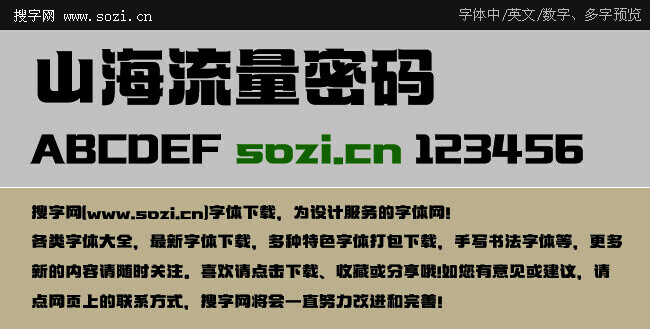
山海流量密碼
搜字網(wǎng)提供一款山海流量密碼中文藝術(shù)字體下載,山海流量密碼是一款醒目的藝術(shù)字體,包含簡體漢字6763個(gè)。該字體線條粗壯醒目,筆畫簡潔自然,字體的視覺效果有力、寬厚、方正,充滿了穩(wěn)重感和設(shè)計(jì)感。具有很好的視覺感。適合包裝設(shè)計(jì)、海報(bào)設(shè)計(jì)、廣告設(shè)計(jì)等應(yīng)用。